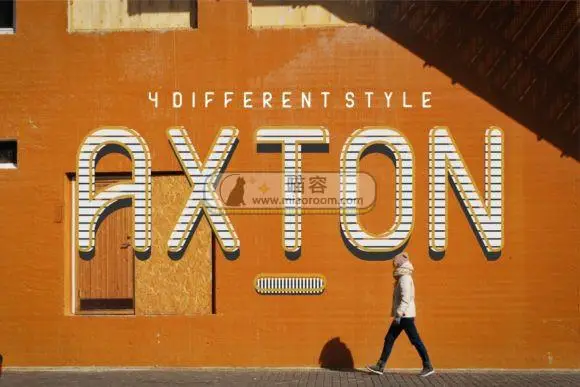
精美字体 21年1月19日 编辑 前往下载 喵容发布2号 取消关注 关注 私信 Axton是一款令人难以置信的圆润无衬线字体,具有现代和简约的感觉。它能让我们的作品脱颖而出。需要的朋友可以到文末进行下载哦! 相关文章: [系统字体] 一款灵感来自动物的字体:本文分享的一款字体(faune)。这款字体是由Alice Savoie在国家艺术中心与Groupe Imprimerie Nationale合作委托的背景下创建的的。该字体灵感来源于动物,并以两部伟大的历史作品为基础。可以说是一款具有 …... [系统字体] 具有特殊边缘的无衬线字体:今天分享的是字体叫做Brisk Pro,它具有非常特殊的边缘特征,在海报制作或者logo设计中非常实用。需要的朋友可以到文末下载哦! 下载权限查看 ¥ 免费下载 评论并刷新后下载 登录后下载 查看演示 {{attr.na …... [系统字体] 实用与独特集于一身的笔刷字体:资源名称 Atmosphere 资源大小 1.07mb 资源格式 ttf、jpg 资源简介 Atmosphere字体具有非常真实的画笔纹理,此字体具有所有大小写字符、数字以及标点。非常适用于品牌设计、包装设计等。 喵容——Atmosphere …... [系统字体] 刷子风格手写字体 MONA字体:资源名称 MONA 资源大小 154kb 资源格式 ttf、jpg 资源简介 Mona是一款手绘笔刷字体,具有对比鲜明的线条。非常适合徽标,海报和包装设计。 喵容——MONA字体1喵容——MONA字体2 下载权限查看 ¥ 免费下载 评论 …... [系统字体] 分层复古字体 BERG字体:资源名称 BERG 资源大小 244mb 资源格式 ttf、png 资源简介 Berg包含一整套大写和小写字母,以及多语言支持,货币数字,数字和标点符号。 喵容——BEGR字体1喵容——BEGR字体2 下载权限查看 ¥ 免费下载 评论并 …... [系统字体]独特的复古字体—Coconut Inline Grunge:资源描述 字体 资源名称 独特的复古字体—Coconut Inline Grunge 资源格式 otf、ttf、jpg 资源大小 619kb 资源简介 这款字体适用于各种印刷项目,徽标,T恤,杂志封面,海报设计等。 可免费用于个人和商业用 …... 下载权限查看 ¥ 免费下载 评论并刷新后下载 登录后下载 查看演示 {{attr.name}}: 您当前的等级为 登录后免费下载登录 小黑屋反思中,不准下载! 评论后刷新页面下载评论 支付¥以后下载 请先登录 您今天的下载次数(次)用完了,请明天再来 支付积分以后下载立即支付 支付以后下载立即支付 您当前的用户组不允许下载升级会员 您已获得下载权限 您可以每天下载资源次,今日剩余次 声明:本文为原创作品,版权归作者所有。未经许可,不得转载或用于任何商业用途。如若本站内容侵犯了原著者的合法权益,可联系我们进行处理。 给TA打赏 共{{data.count}}人 人已打赏 axton字体下载无衬线现代简约